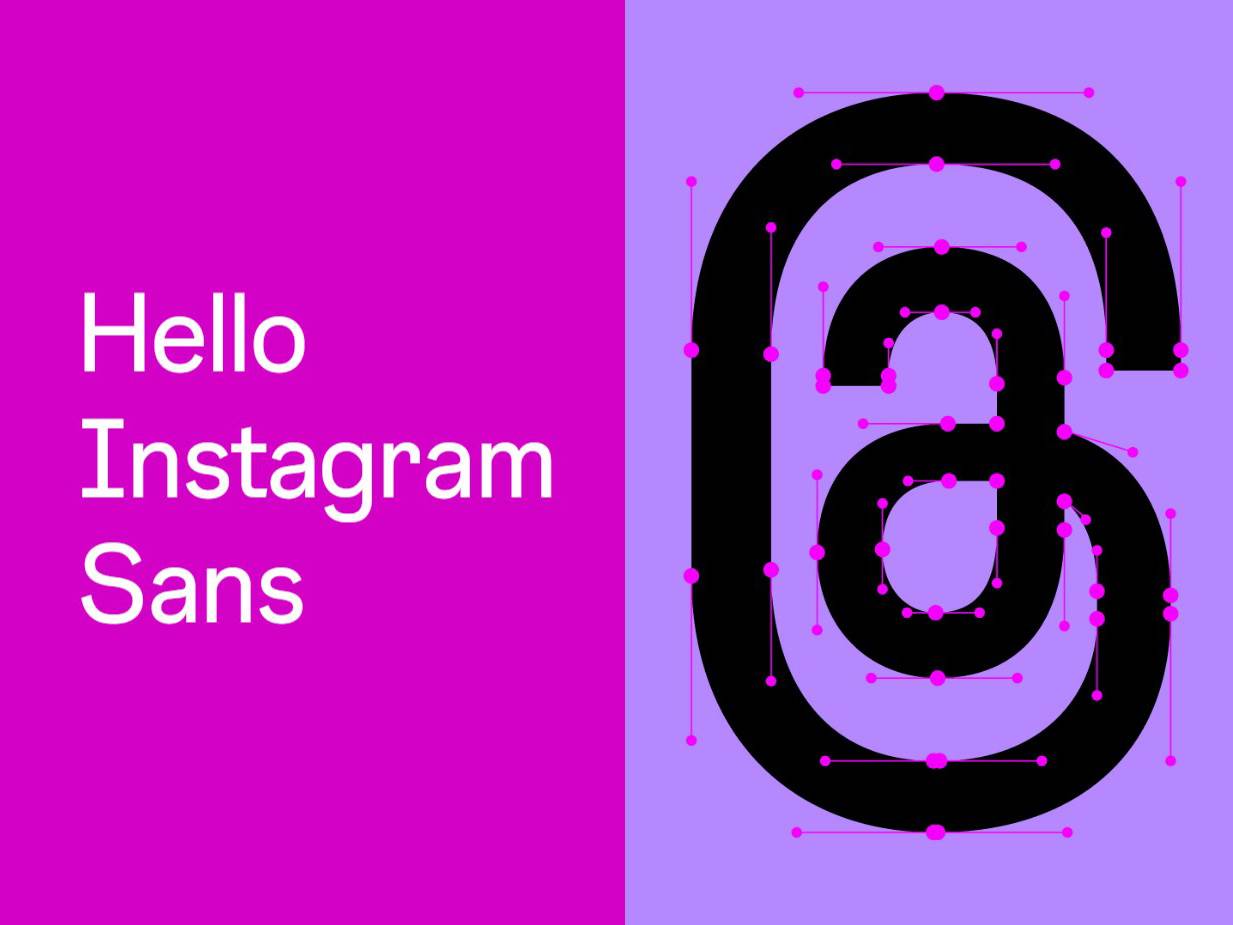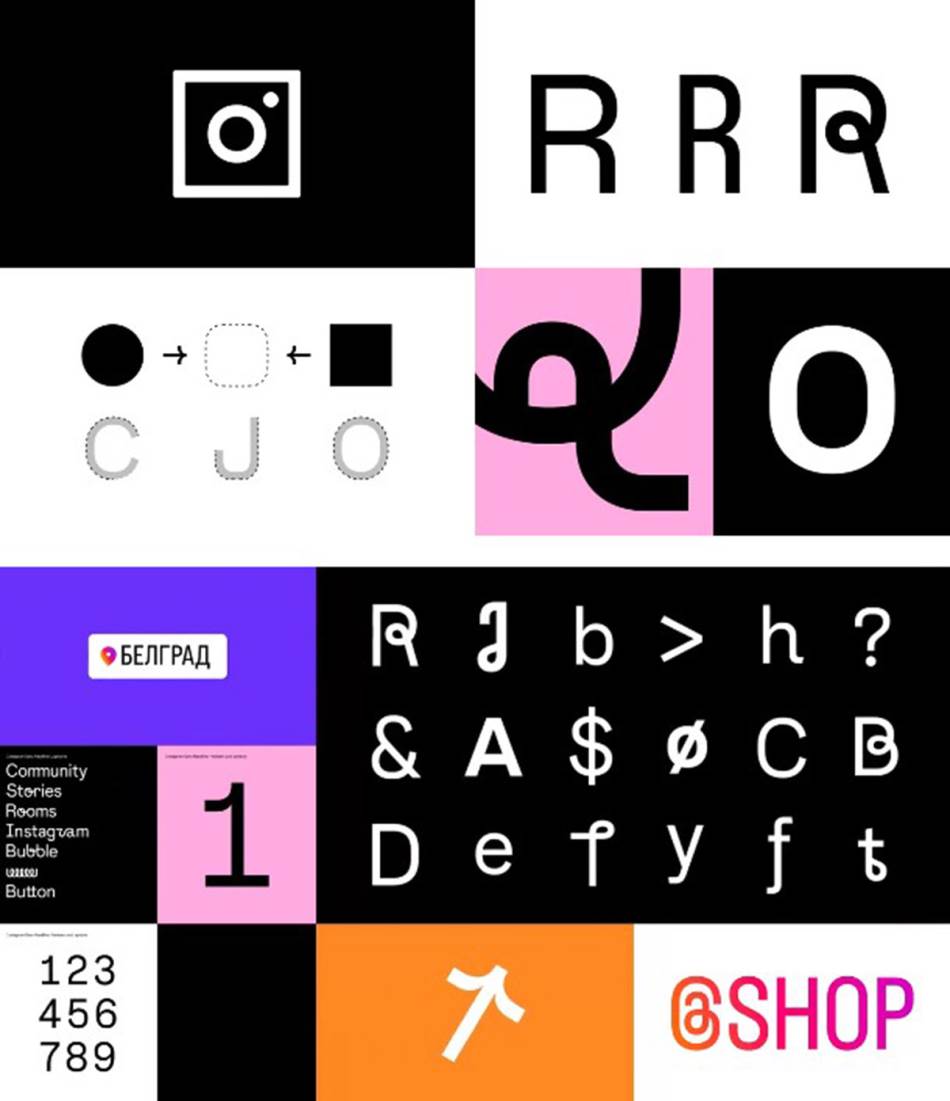
INSTAGRAM MENJA IZGLED: "Vizuelno osveženje", novi font namenjen svim jezicima
Instagram donosi novi izgled za "sveobuhvatnija i inkluzivnija iskustva"
Instagram je najavio da uvodi “vizuelno osveženje“ za svoj brend. Kompanija uvodi blago izmenjen logo, novi font i marketinške rasporede preko celog ekrana. U saopštenju kažu da je osveženje osmišljeno da “stvori sveobuhvatnija i inkluzivnija iskustva.“
Novi font se zove “Instagram Sans“ i inspirisan je logotipom kompanije, odnosno kvadratima, krugovima i zaobljenim oblicima. Font takođe sadrži više globalnih skripti. Kompanija kaže da je "Instagram Sans" savremeni remiks grotesknih i geometrijskih stilova.
“Instagram Sans je novi način da se naša globalna zajednica izrazi na Instagramu, na mestima kao što su Stories i Reels“, saopštila je kompanija. “Dok smo dizajnirali novi font, cilj nam je bio da Instagram Sans učinimo globalno dostupnim. Udružili smo se sa stručnjacima za jezike širom sveta, kako bismo prilagodili font globalnim pismima, uključujući arapsko, tajlandsko i japansko. Želimo da podržimo sve naše kreatore i članove zajednice, koji guraju kulturu napred, da se u potpunosti izraze na bilo kom jeziku.“
Instagram novi font Izvor: Instagram
Što se tiče novog logotipa, gradijent je sada malo življi da bi izgledao “osvetljenije i življe“, kaže kompanija. Instagram napominje da je gradijent iznova zamišljen korišćenjem procesa 3D modelovanja.
Marketinški raspored, za koji instagram kaže da je dizajniran da “slavi jednostavnost“, je predstavljen korisnicima u momentu kada Instagram testira novi izgled sadržaja, nalik TikTok aplikaciji.